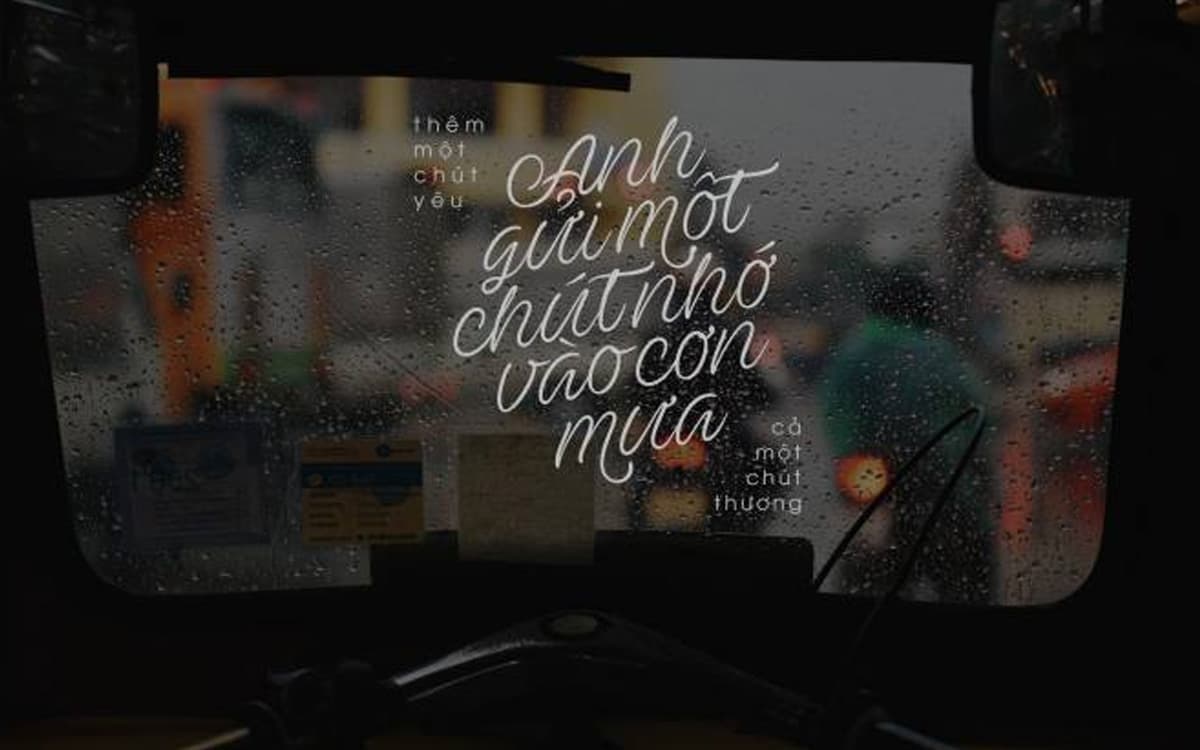
Ave Utan là một font chữ viết tay mang đậm chất thủ công, toát lên vẻ đẹp mộc mạc và tự nhiên. Thuộc dòng chữ Script, Ave Utan sở hữu những đường nét mềm mại, uyển chuyển, tạo nên một cảm giác gần gũi, chân thật. Với sự đa dạng về phong cách, Ave Utan là lựa chọn hoàn hảo cho những thiết kế cần sự ấm áp, cá tính và một chút gì đó nghệ thuật.
Việc được Việt hóa đã giúp Ave Utan trở nên linh hoạt hơn trong việc đáp ứng nhu cầu thiết kế đa dạng. Từ thiệp mời, bao bì sản phẩm, đến các ấn phẩm truyền thông, Ave Utan đều thể hiện được nét đẹp riêng biệt. Mỗi nét chữ như một câu chuyện, mang đến cho người xem những cảm xúc chân thật và ấm áp.
Với Ave Utan, bạn có thể tạo ra những thiết kế mang đậm dấu ấn cá nhân, truyền tải thông điệp một cách tinh tế và hiệu quả. Hãy để Ave Utan đồng hành cùng bạn, tạo nên những tác phẩm thiết kế độc đáo và ấn tượng.